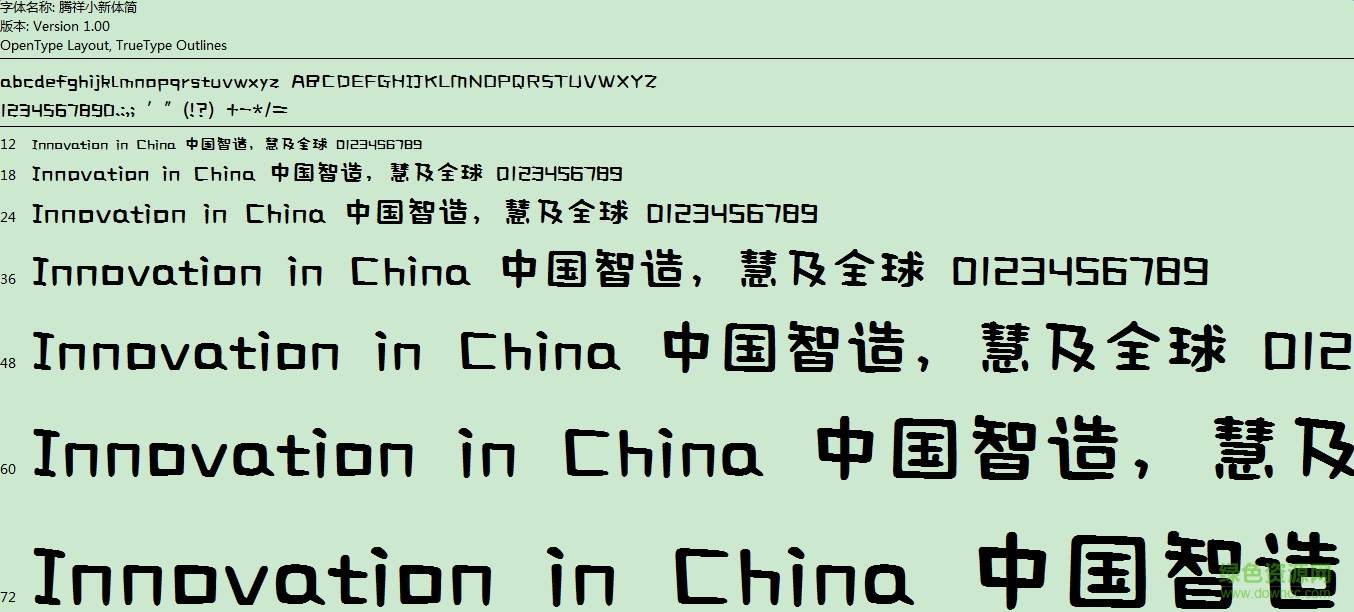
騰祥小新體簡(jiǎn)是一款騰祥出品的簡(jiǎn)體字體,美工設(shè)計(jì)、海報(bào)廣告設(shè)計(jì)、藝術(shù)設(shè)計(jì)等方面都可以使用,小編為大家?guī)?lái)免費(fèi)下載地址,大家快來(lái)綠色資源網(wǎng)踴躍下載哦!
騰祥小新體簡(jiǎn),一款非常工整舒暢的字體,文字排版也可以使用喲,溫潤(rùn)自得。